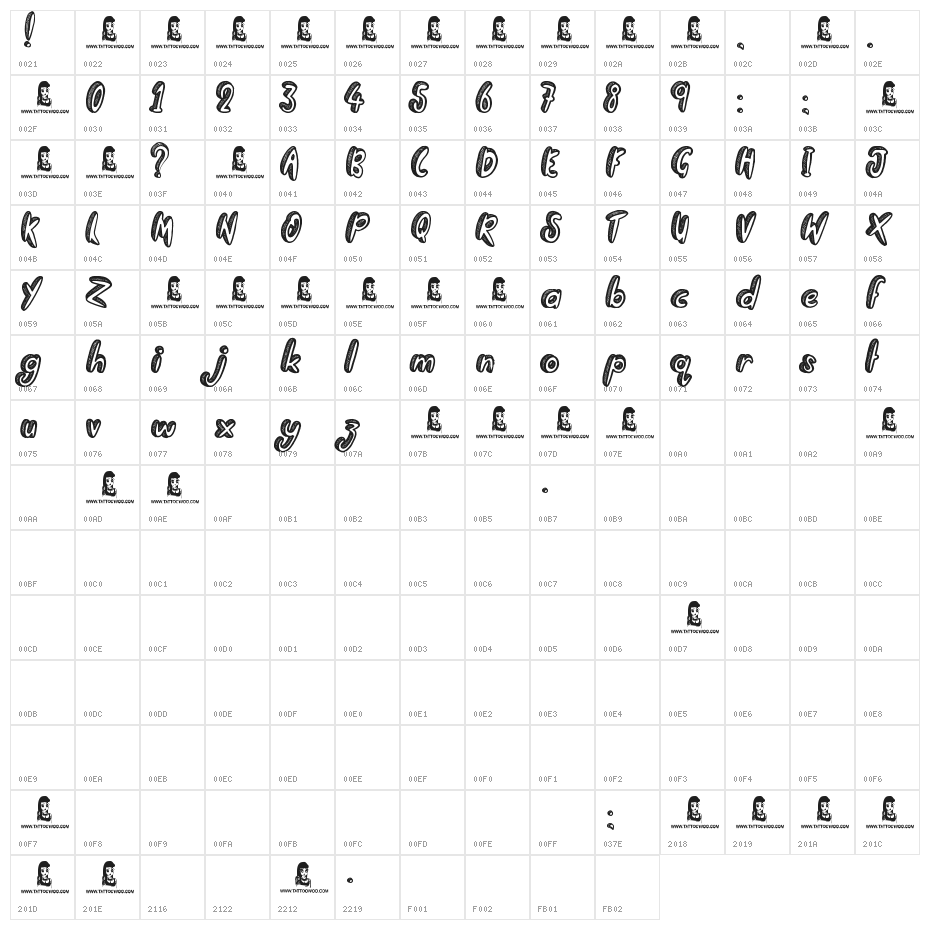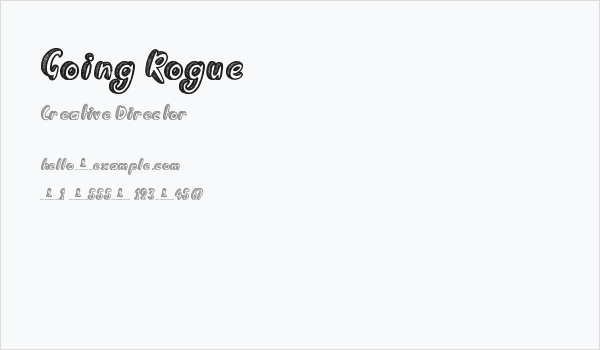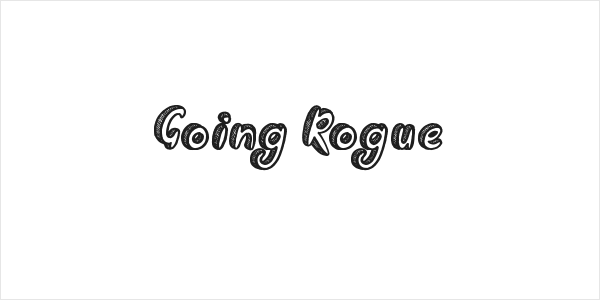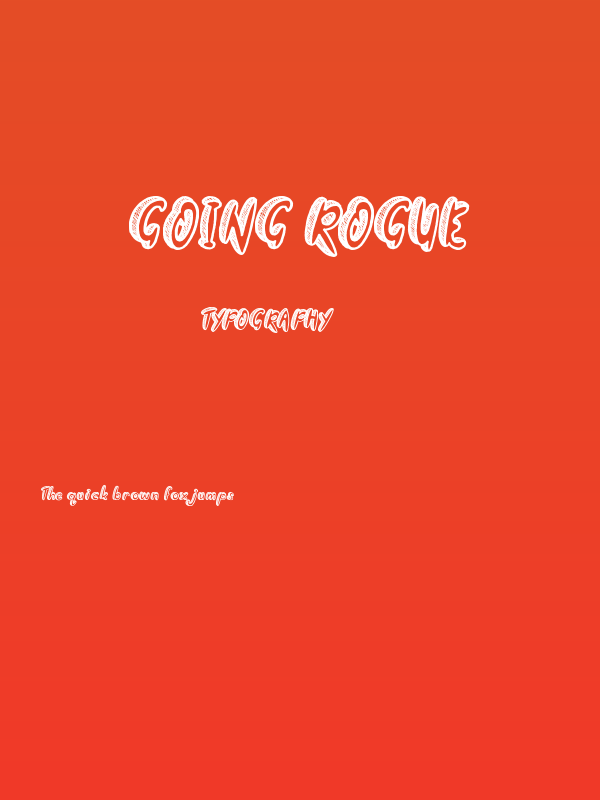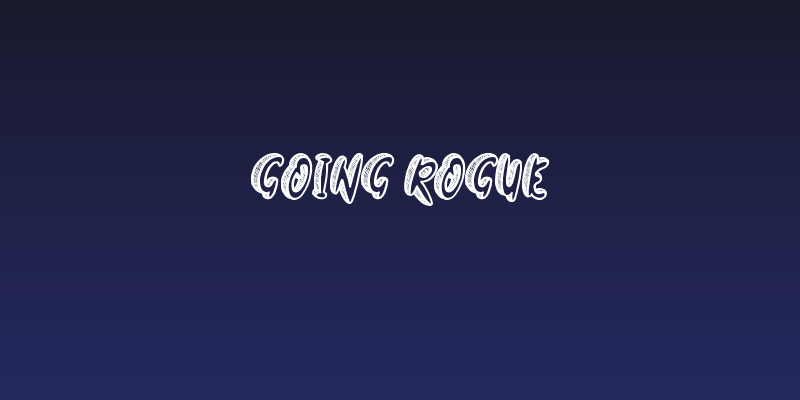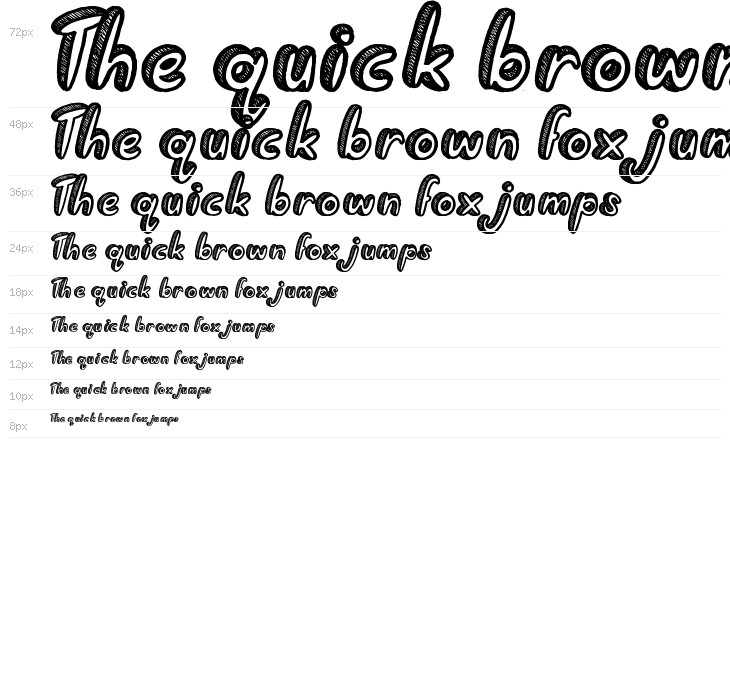
Going Rogue Font
| Stile generale | Playful, Hand-drawn, Casual |
| Progetti proposti | Ideal for children's books, comic strips, playful branding, and casual invitations. |